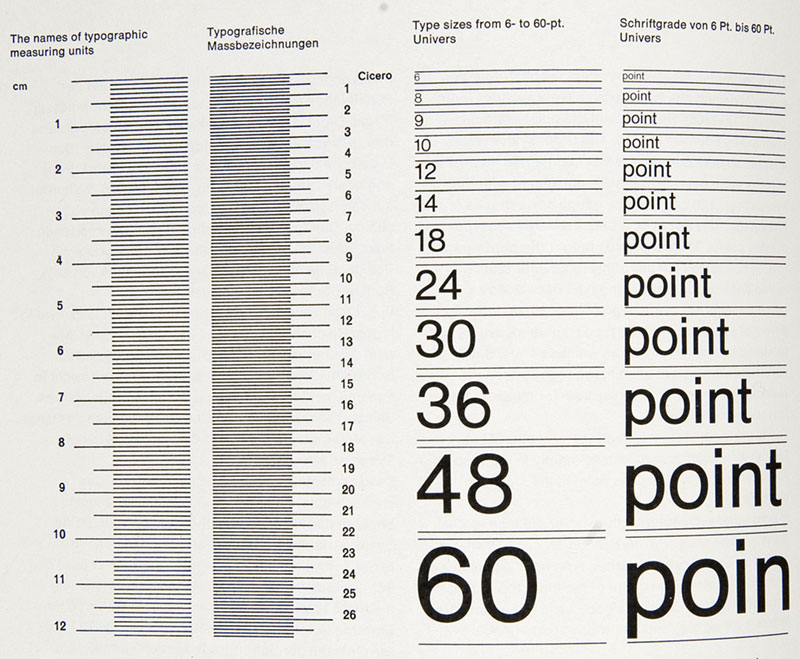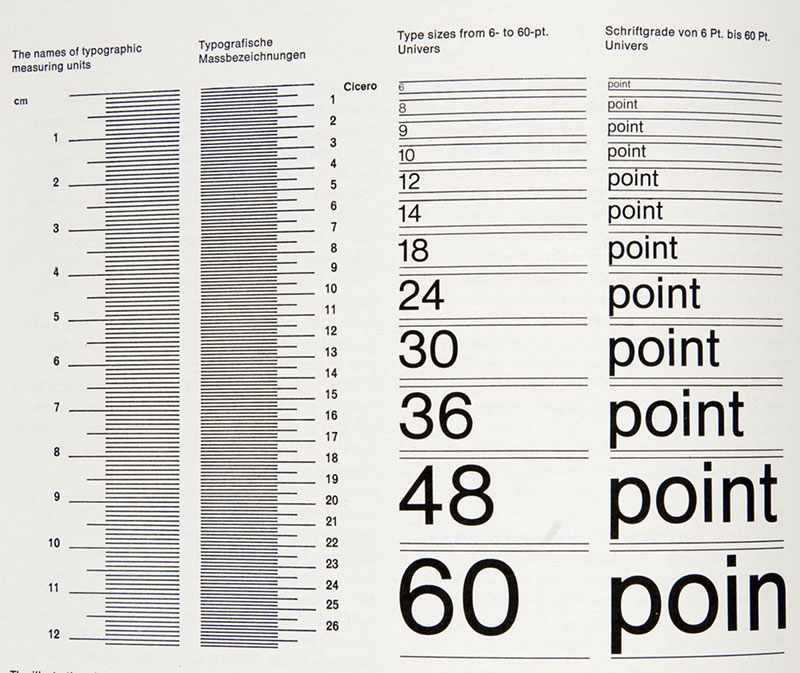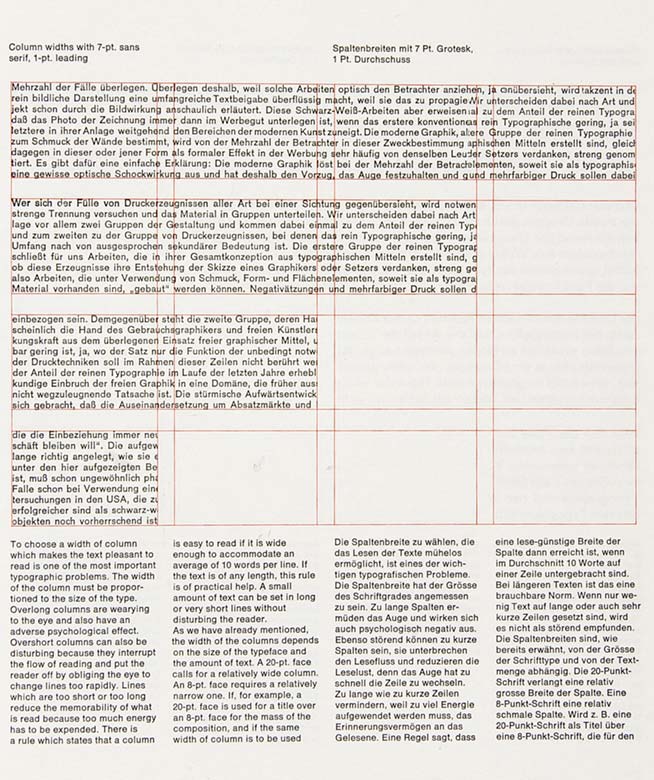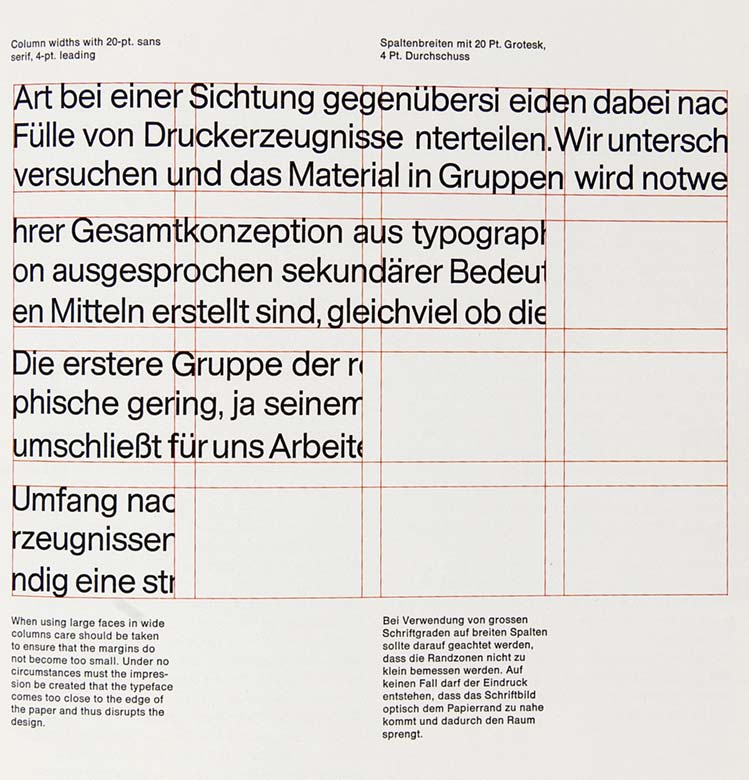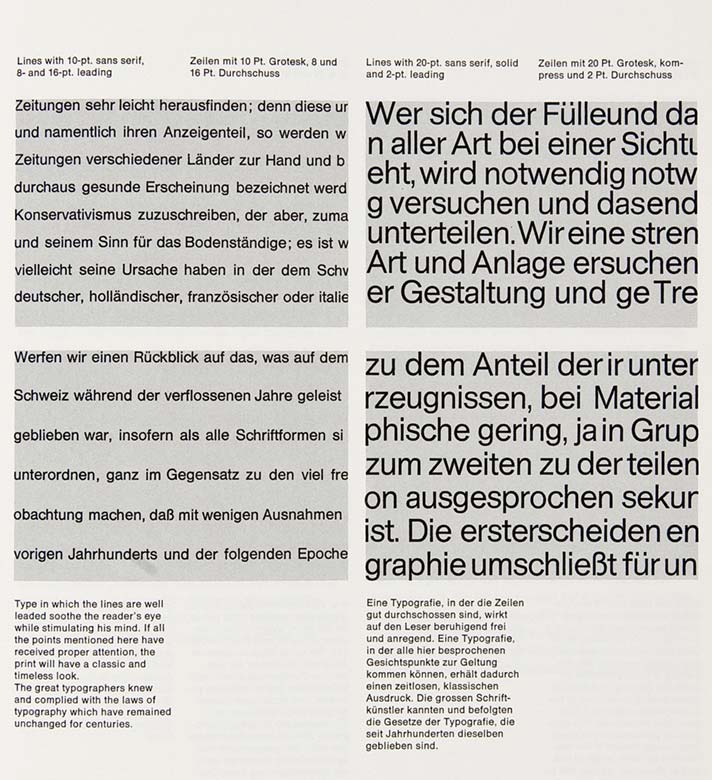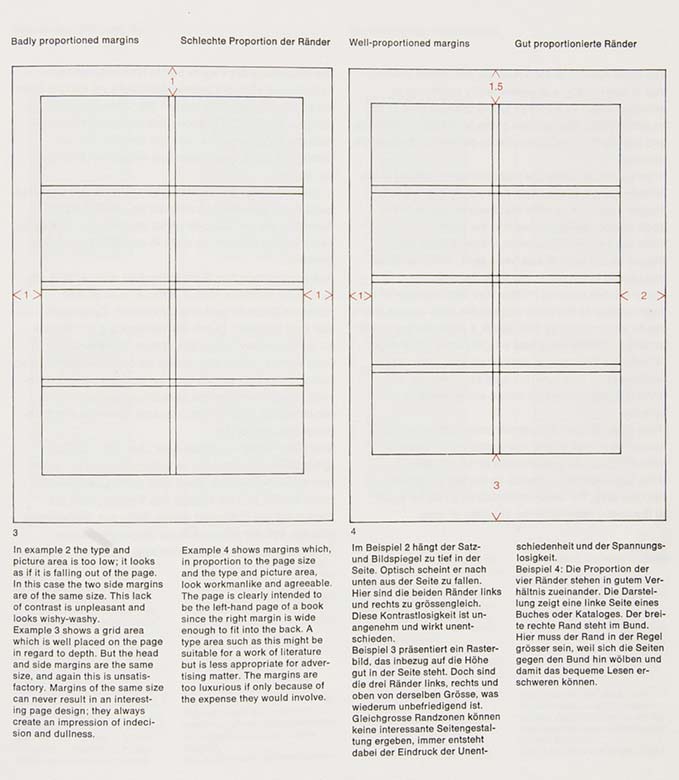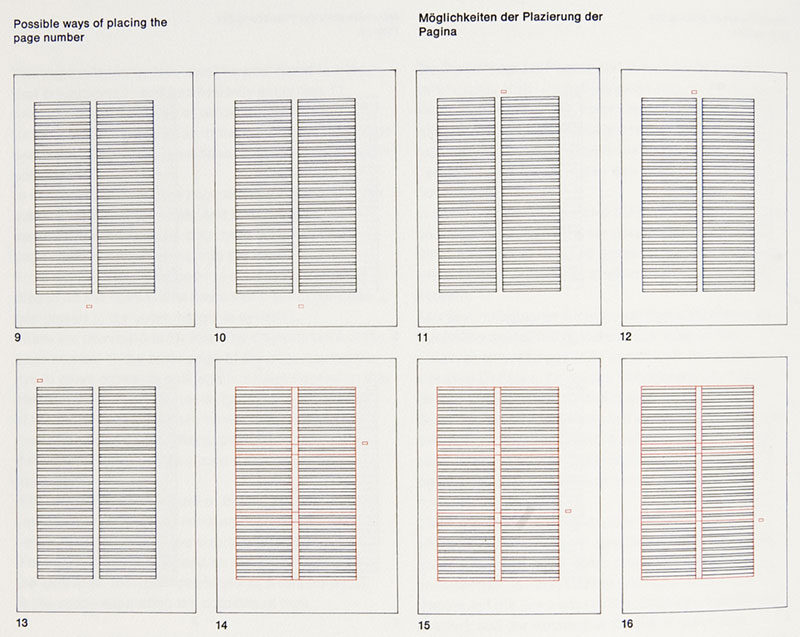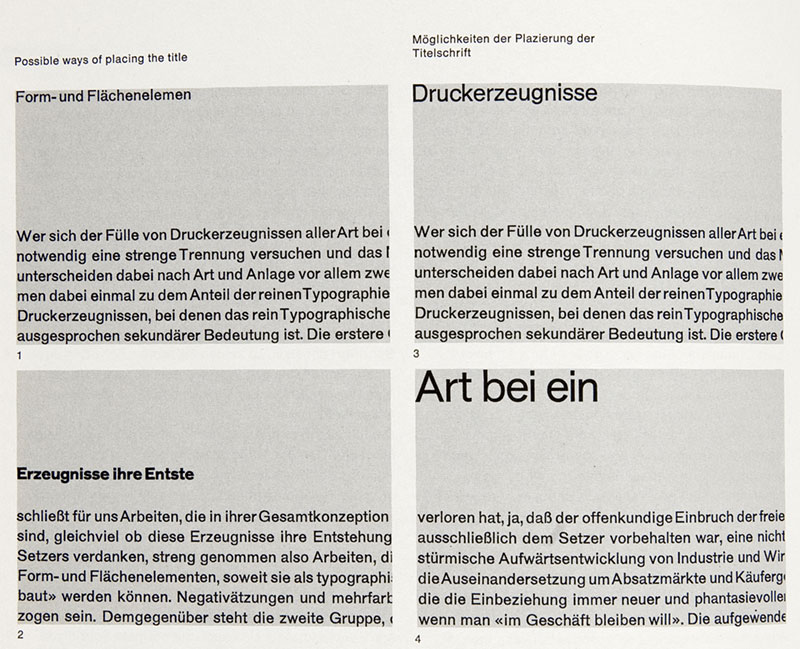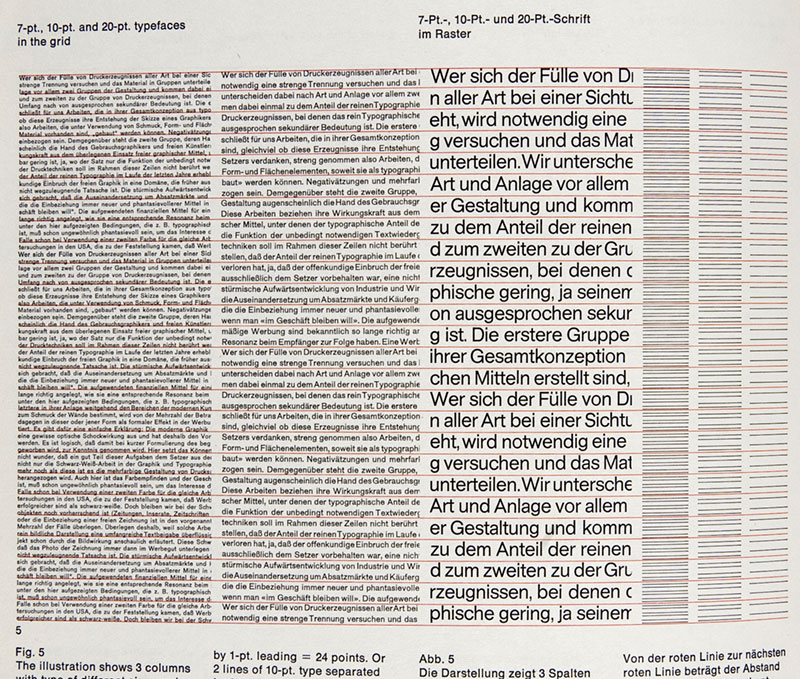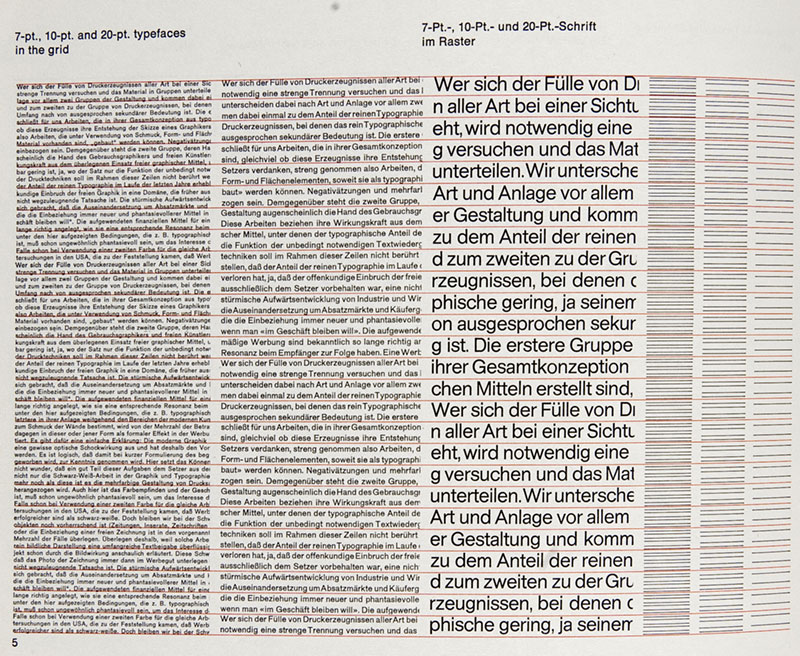
Grilles de Mise en Page | typoGraphie Web et Papier
C’est Josef Müller Brockmann
qui a jeté les bases
d’une explication
détaillée sur le sujet.
L’histoire des grilles de mise en page se confond aisément avec celle de la mise en scène typographique depuis l’invention de l’alphabet moderne par les phéniciens quelques 700 ans avant JC.
Johannes, le grand Gutenberg, inventeur de la lettre mobile et «inter-active» en plomb et antimoine, utilisait déjà deux colonnes dans sa bible en 42 lignes au XVe siècle. Sans doute que les imprimeurs avaient saisi assez tôt la nécessité de renvoyer le lecteur à la ligne lorsque la ligne dépassait quelques 40 signes. De fait les études sur le confort de la lisibilité donnent un variable assez large, cela va de 30-40 signes jusqu’à quelques 60 caractères par ligne. Ce qui correspond en somme à la largeur d’une colonne unique dans un courrier composé en corps 12.
Le développement des formats de la presse, bien plus gigantesques que ceux du livre ont posé rapidement le problème de l’organisation des pages. Non seulement pour des raisons de confort pour la lecture mais également pour la gestion des espaces pour la Réclame, puis plus tard de la Publicité. L’organisation en colonne est donc née fin du XVIIIe siècle, alors que Marat immergé dans sa baignoire ensanglanté participait à la naissance de la presse révolutionnaire (l’Ami du Peuple).
À l’heure où je vous parle cette organisation n’est plus contestée et participe non seulement à la qualité de la lecture des journaux, mais également et paradoxalement à une codification, à une architecture sémantique de la mise scène de la presse quotidienne. Autrement dit, lorsqu’un journal se crée, ou se relift, il n’est pas seulement de bon ton de l’organiser en grille et colonne, pour faciliter sa lecture, mais de lui donner une forme graphique qui l’installe dans le paysage codifiée d’une presse séculaire.
Vous invite donc à découvrir ces quelques “extracts” des pages de l’ouvrage de Josef Müller Brockmann qui nous expliquent le fonctionnement et la structuration d’une page (d’édition ou de presse), livre que je ne saurais que trop vous recommander de vous procurer sur les sites d’Amazone ou de l’éditeur. Brockmann prend le contre-pied d’Hermann Zapf, qui explique par l’exemple et une pratique de l’édition héritée de la plus grande tradition. Ici, le graphiste-professeur, d’origine suisse énonce les règles strictes et quasi mathématiques de l’organisation d’une page. Architecture et architexture comme je l’ai déjà souligné plusieurs fois cohabitent pour ordonner et donner à lire… (suite du billet dans la journée).
L’intérêt de cet ouvrage est d’aligner page après page, de manière exhaustive les variations de structures verticales et horizontales, de montrer comment les blancs doivent dans chaque cas s’organiser, et surtout d’insister sur la texture typographique qu’engendrent les solutions de découpage. Corps et interligne sont au centre de ces réflexions pragmatiques… vous réduisez la colonne, le nombre de signe par ligne doit suivre homothétiquement donc le corps doit diminuer. L’interlignage de même, participe de la lisibilité des colonnes et Brockmann donne les clés de ces variations.